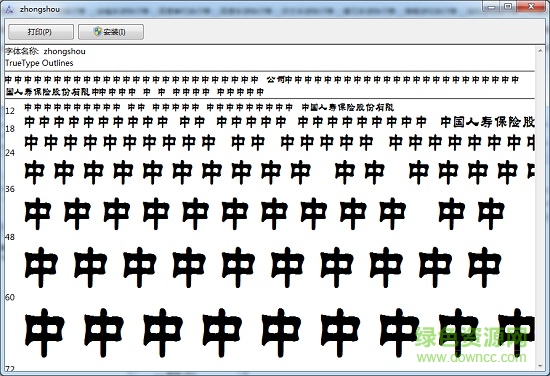
中國人壽保險字體是一款非常好用的字體,是中國人壽內(nèi)部的一款字體,非常的剛勁有力,筆畫清晰簡潔,歡迎喜愛的朋友到綠色資源網(wǎng)下載使用!
字體中只包含“中國人壽保險股份有限公司”這幾個字,使用時請輸入0123456789AB這些字母,然后在字體列表里選擇“zhongshou”,就可以輸出這些字了。方便大家使用!